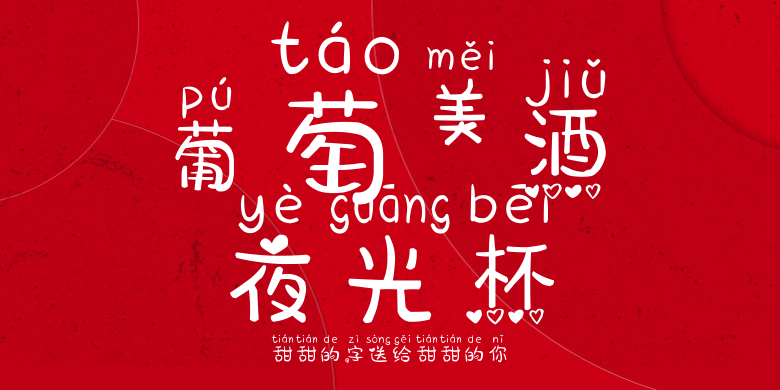
甜甜的字送给甜甜的你
甜甜的字送给甜甜的你,这款字体结构工整、笔画清晰,兼顾美观与易读性,适用于标题、正文、海报、包装、LOGO 等多种场景。字形优雅稳定,风格百搭耐看,适配日常排版与创意设计,让文字呈现更舒适、更具质感。甜甜的字送给甜甜的你一笔一画,皆是细节,以均衡的比例、流畅的线条打造舒适视觉体验,字形端正大气,风格简约现代。无论是商业设计、品牌宣传还是日常排版,都能轻松驾驭,让文字更有格调与力量。甜甜的字送给甜甜的你字体下载。